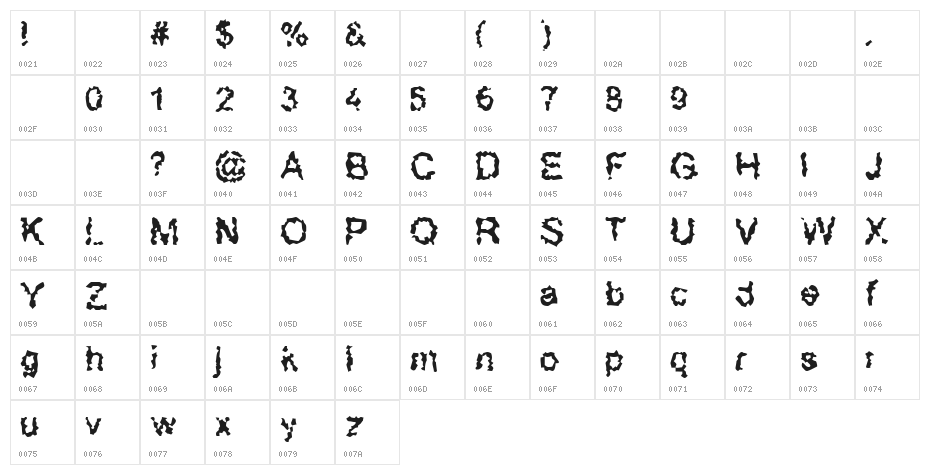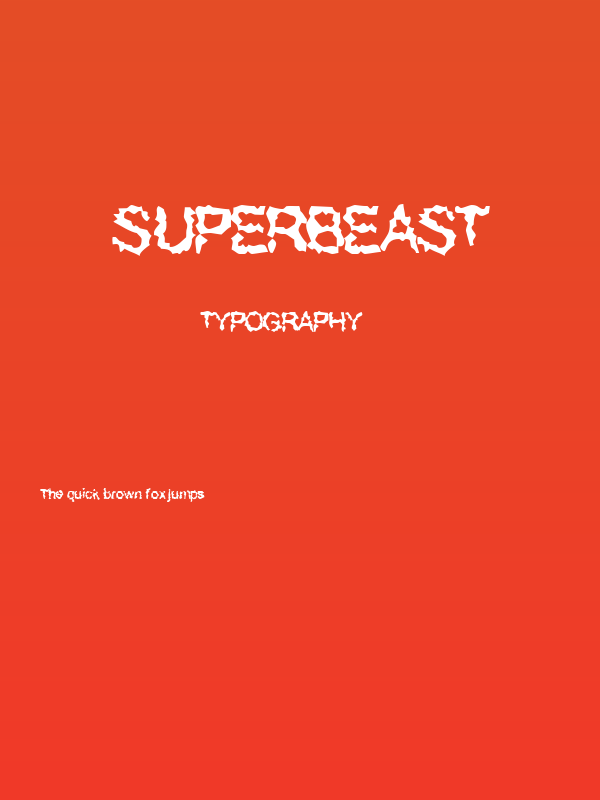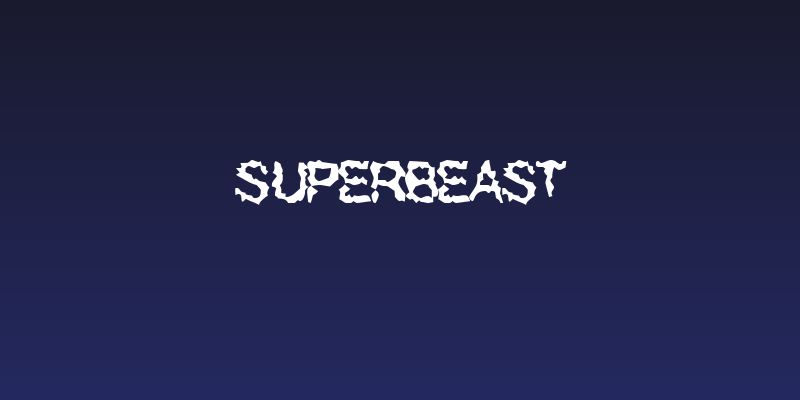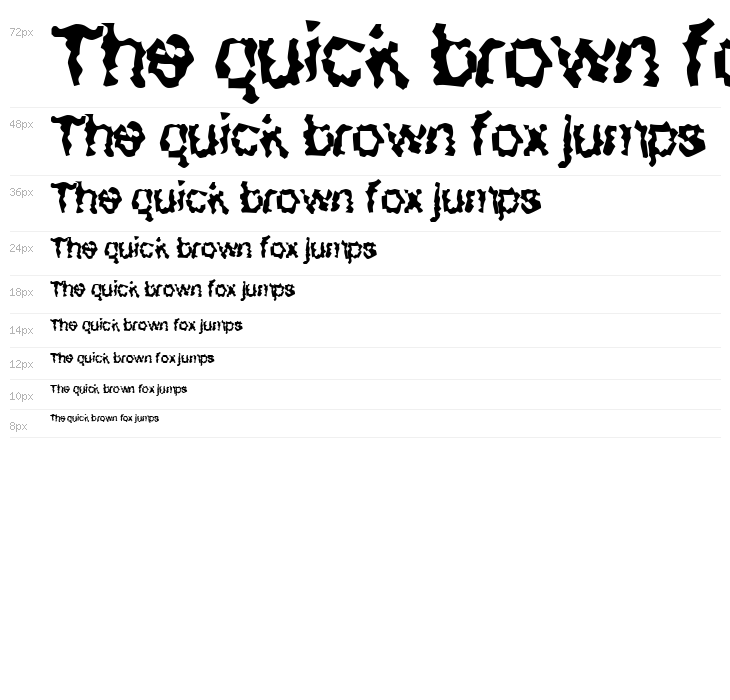
Superbeast Font
✎ Messy
| Vorgeschlagene Projekte | Perfect for album covers, horror movie posters, edgy branding, or any project needing a bold, gritty aesthetic. |